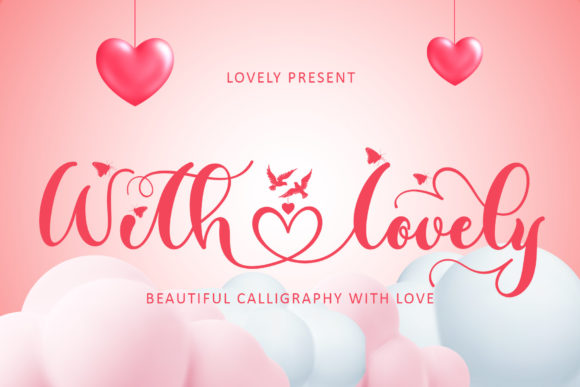
With Lovely
With Lovelyのような高品質の素材をお探しの場合、このプレミアムパッケージはクリエイティブなプロジェクトに素晴らしい選択です。
POD(オンデマンド印刷)製品、結婚式の招待状、またはソーシャルメディアのグラフィックを作成している場合でも、With Lovelyは理想的です。